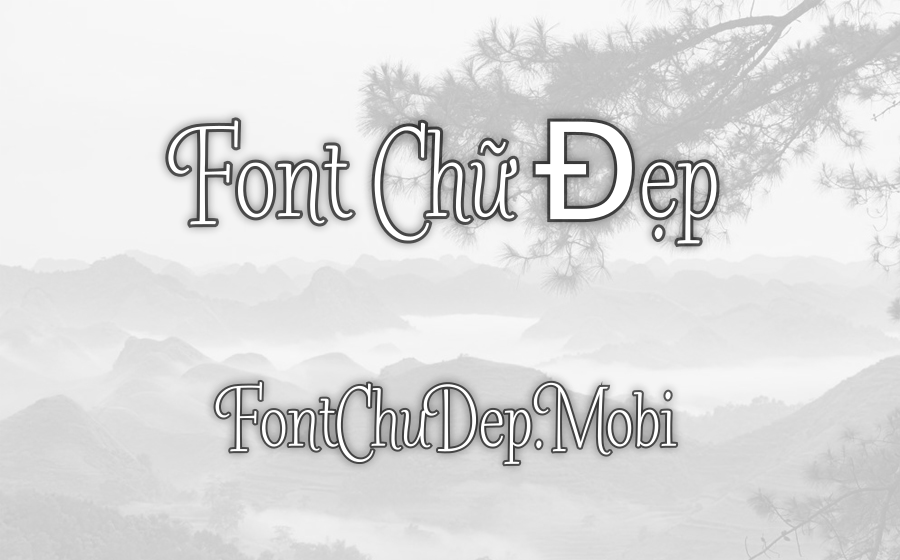
UVF Barmbrack là một phông chữ serif mang một phong cách riêng biệt mà tôi đã có cơ hội tiếp xúc và trải nghiệm. Với nét đẹp cổ điển kết hợp cùng các đường nét tinh tế và giàu sức sáng tạo, phông chữ này đem đến cho tôi cảm giác thực sự trang nhã và quý phái. Một đặc điểm tuyệt vời của UVF Barmbrack là khả năng linh hoạt, phù hợp cho nhiều dự án thiết kế khác nhau như tiêu đề, logo, bao bì sản phẩm cũng như các ấn phẩm in ấn khác. Điểm đặc biệt là phông chữ này đã được thu thập và chia sẻ bởi các thành viên của FontChuDep.mobi, một cộng đồng nổi tiếng với những đóng góp giá trị trong việc giới thiệu những font chữ đẹp và độc đáo.
Font UVF Barmbrack Việt Hóa
UVF Barmbrack